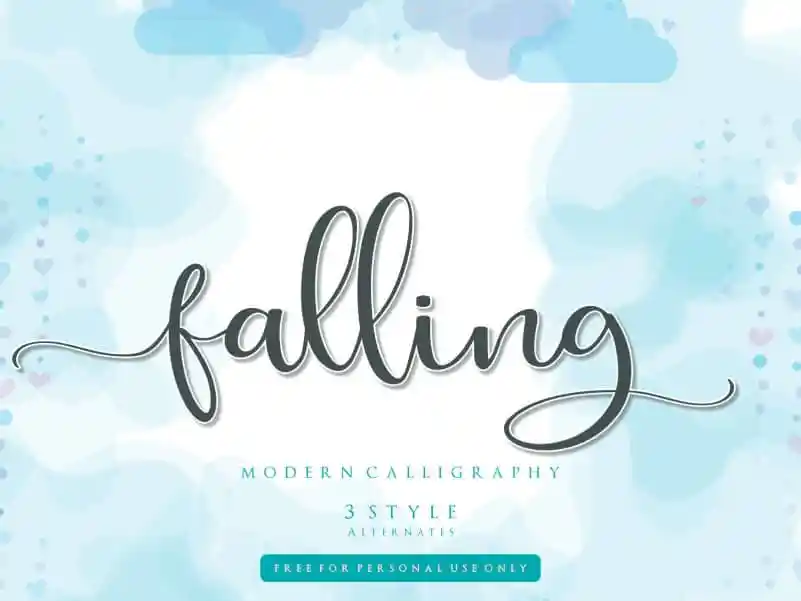
Falling Calligraphy Font – Download Grátis
A Falling Calligraphy Font é uma escolha inovadora para quem busca trazer um toque atraente à suas criações digitais. Desenvolvida pelo designer Nuryanto Dwi, essa fonte carece e bateada se destaca pela sua versatilidade. Ela oferece linhas suaves e fluidas que prometem transformar qualquer ideia criativa em uma verdadeira obra de arte, seja para uso no Instagram ou na concretização dos seus projetos DIY. Seja você um designer de perfil digital buscando um texto agradável para suas postagens nas redes sociais, ou alguém com habilidades artísticas que deseja dar vida à sua próxima reconstituição de uma escrita antigua em papel, essa fonte será seu aliado perfeito. Ela não apenas tornará seus projetos mais atraentes, mas também adicionará um toque único e autêntico aos mesmos. Junte-se a esta fonte cuidadosamente criada e transforme suas ideias em realidade com Falling Calligraphy Font.